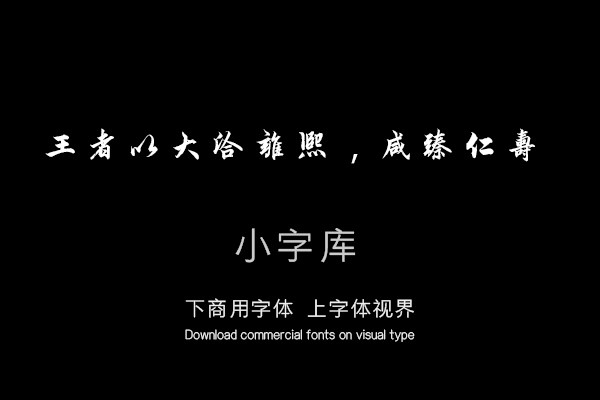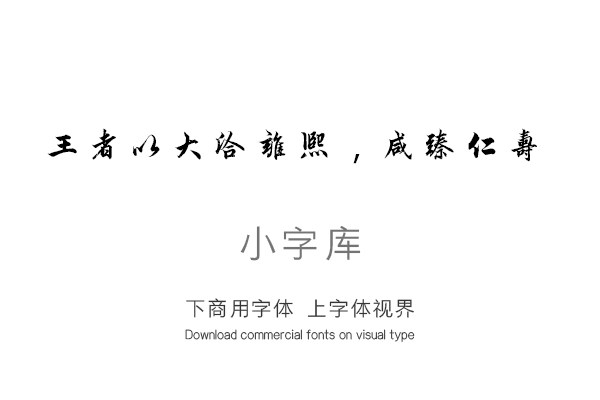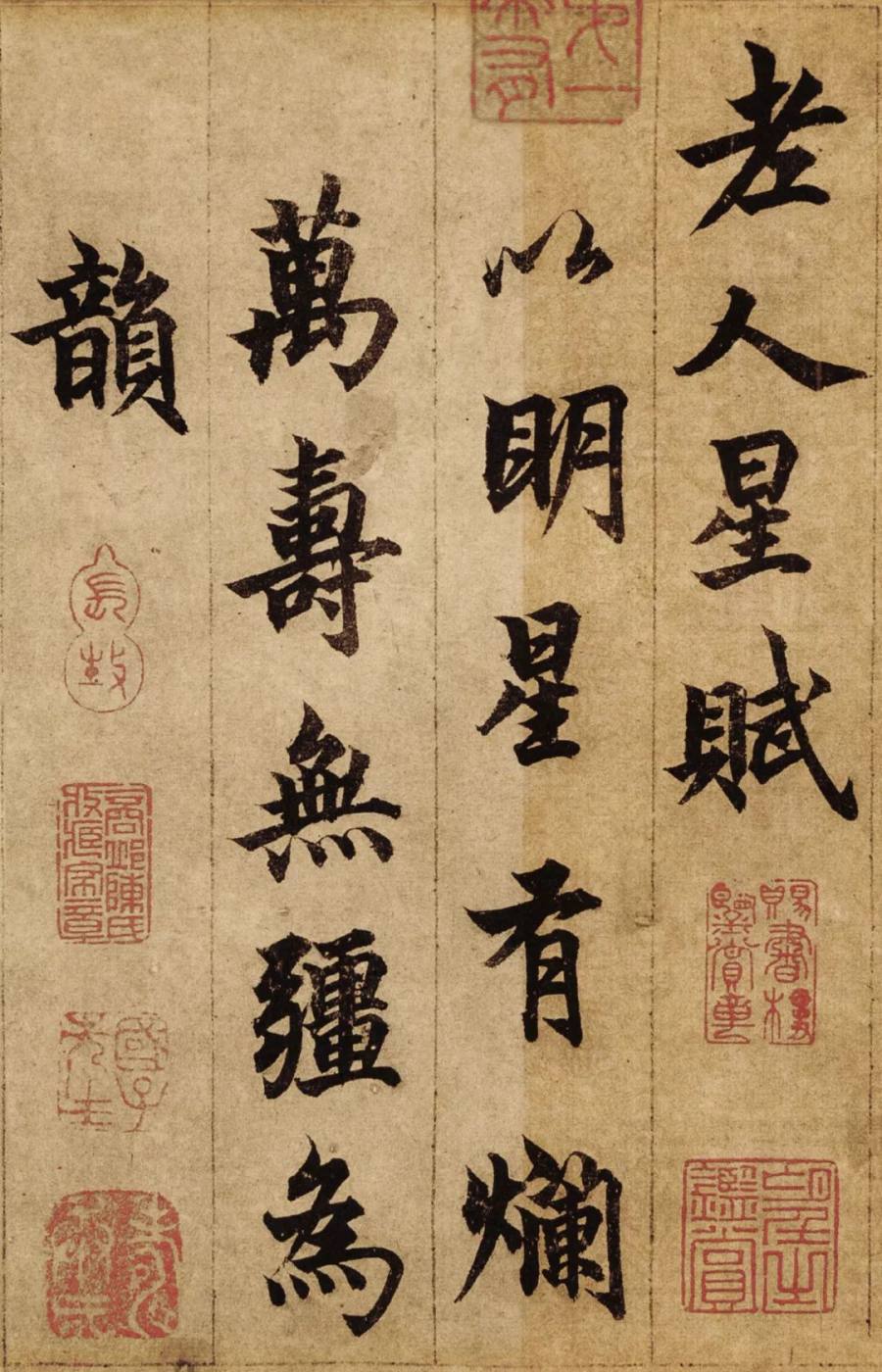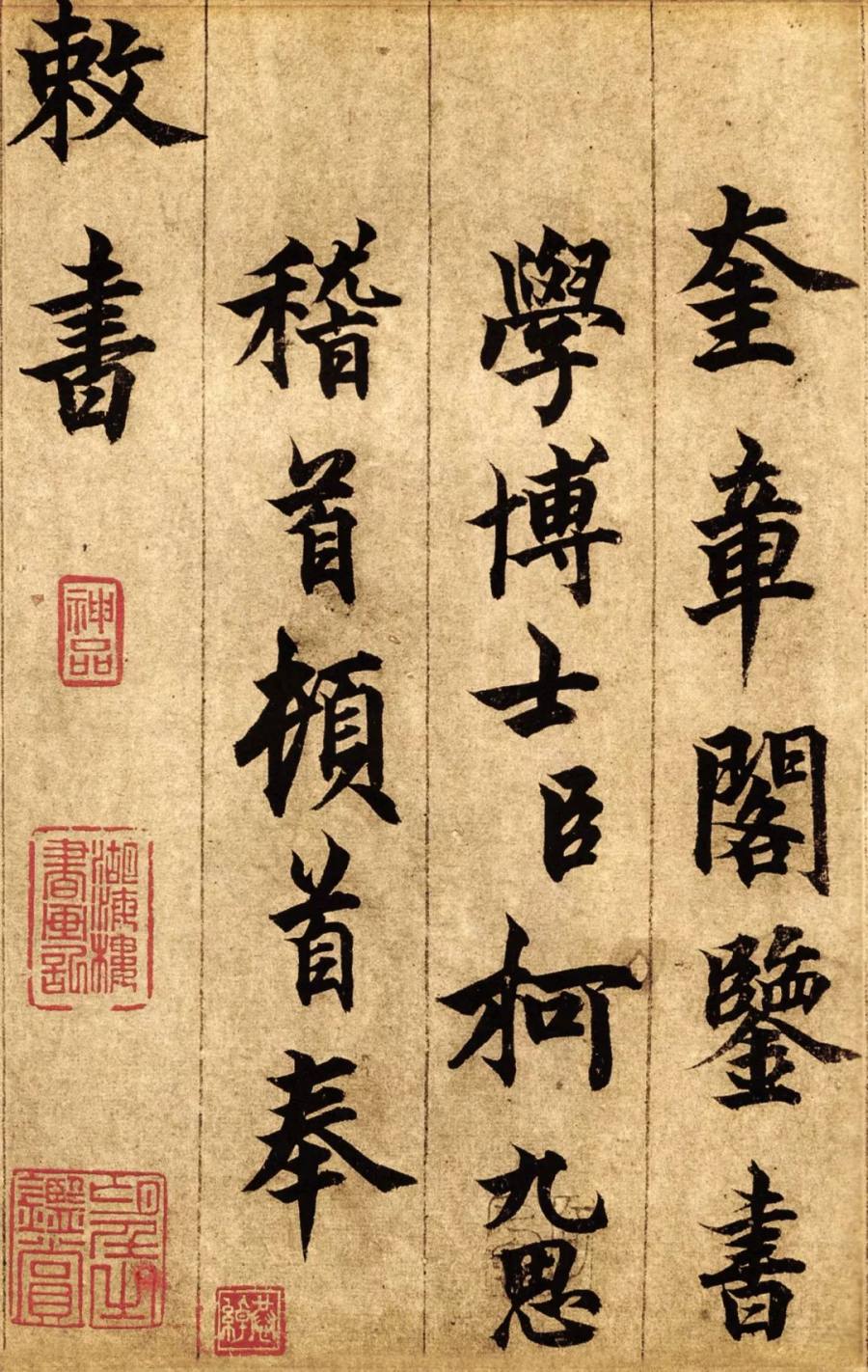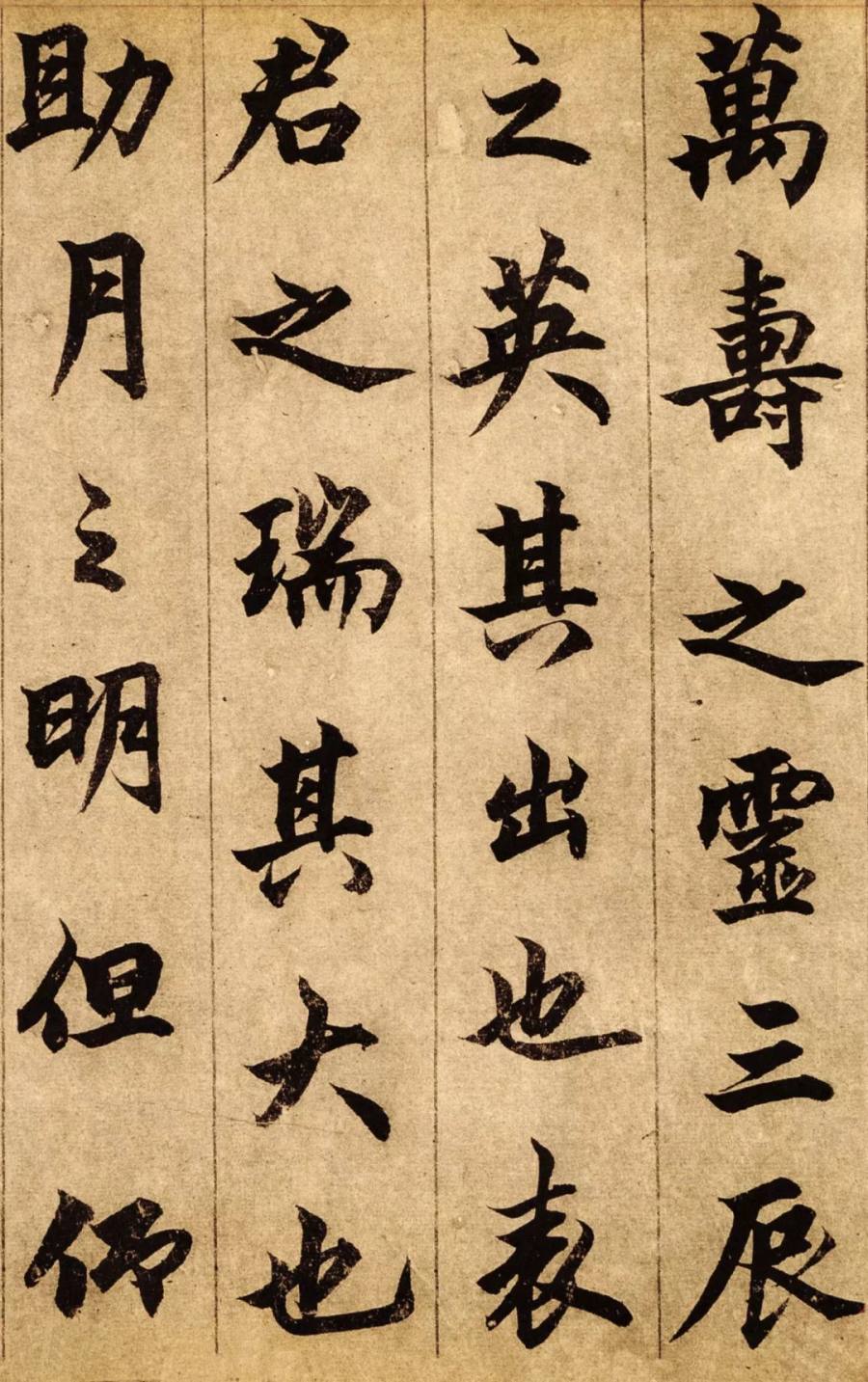
《汉标柯九思行楷老人星赋》是一款根据元朝书画家,柯九思《老人星赋》长卷,经过再次调整制作的小字库,该小字库共收录了该真迹作品中约530个字体。单字授权
《老人星赋》以“明星有烂,万寿无疆”为韵。奎章阁鉴书,学博士臣柯九思稽首顿首奉敕书。万寿之灵,三辰之英。其出也,表君之瑞;其大也,助月之明。但仰祥光,莫辨皤然之象;方资睿算,斯垂耄矢之名。王者以大洽雍熙,咸臻仁寿;感垂象之丕变,彰御国之可久。爰假号扵耆年,寔归美于元后,南郊享处,能无鼓缶之歌?银汉经时,旌是游河之友?观夫落落位正,荧荧影孤。应春秋之候,出丙丁之隅。视合璧之祥兮未异,顾连珠之瑞兮若无。象兹黄发,永我鸿图。想天上之宵征,宁悲钟漏;顾人间之夕景,岂恨桑榆。是何上象著明,曷时合偶。历数自延于人主,名实何惭扵国叟。月轮遥睹,安车之意宁无?天驷旁瞻,失马之嗟何有?此盖君著明德,天陈瑞星。会兹鼎盛,荐乃椿龄。增芳华扵信史,协休美于祥经。每睹运行,如纵心扵黄道;无差躔次,凝尚齿扵青冥。足使观象者考祥,占天者改观。挂碧空而的的,度青霄而烂烂。非时不见,如四皓之避秦;有道必居,若二疏之在汉。大矣哉,名尊五福,位列三光。发天之炳焕,苻帝德之悠长。北阙前瞻,独呈祥扵有烂;南山俯映,共斯寿于无疆。士有仰而赋曰:“天之象兮示劝,君之位兮善建。实赞天灵之数,允叶华封之愿。又何必周王之梦九,而嵩岳之呼万者也?”共和丙寅得于京师;恭绰;吸欧李之精英为赵虞之劲敲。